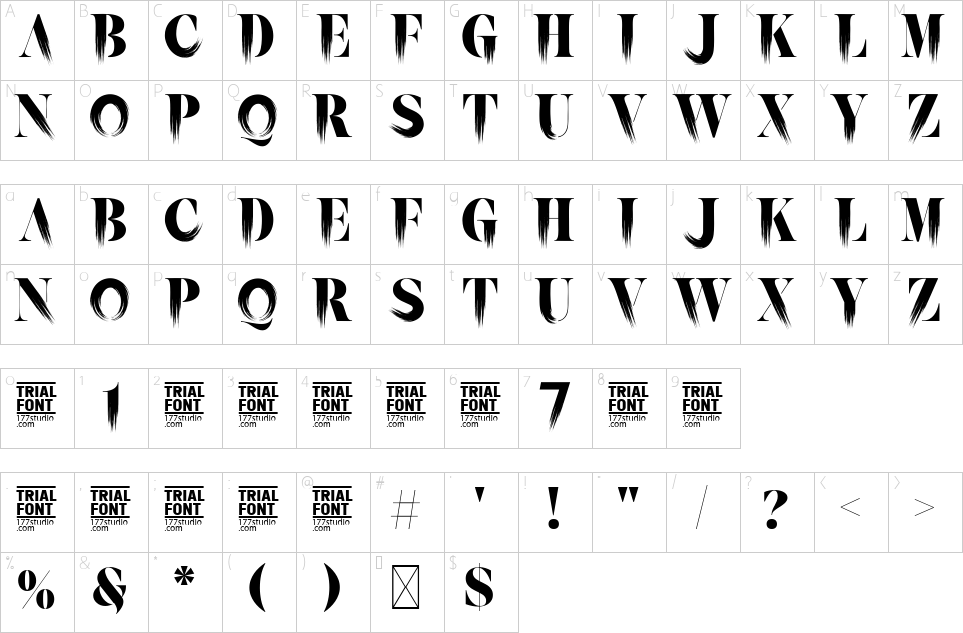
A Drama Genre Font é uma elegante escolha para quem busca estilos poderosos e dramáticos no design de escrita digital. Essencialmente criada por 177studio.com, esta fonte está disponível tanto para Windows quanto para Mac, dando a você um amplo leque de opções. Com seu risco contínuo e linhas marcantes, essa fonte destaca-se como uma ótima escolha para headlines e textos dramáticos em qualquer aplicação digital ou impressa. Com apenas 6,679 downloads, a Drama Genre é um tesouro que merece ser explorado e experimentado. Tornando seu design mais criativo e sofisticado do que nunca!